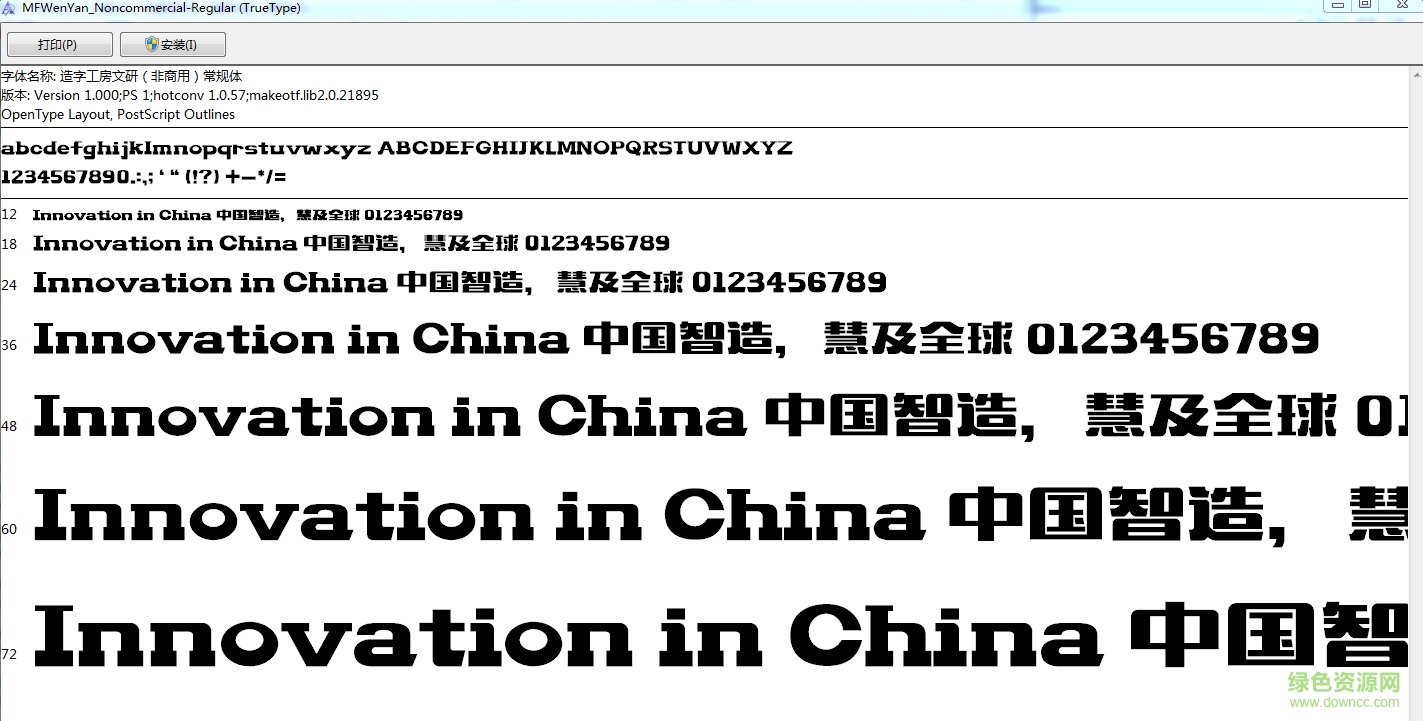
造字工房文研體是一款造字工房類粗黑風(fēng)格字體軟件,文研體給人非常古典浪漫的感覺(jué),十分醒目,適合各大標(biāo)題設(shè)計(jì),也深受廣大書法家的喜愛(ài),還有更多好看字體盡情期待,歡迎到綠色資源網(wǎng)下載體驗(yàn)!
造字工房文研體字形筆畫粗大、平直,讓整體字形更顯干練!精細(xì)的筆畫間凸顯匠師精雕細(xì)琢之力,柔中兼剛不失韌勁。是一款獨(dú)具特色的字體產(chǎn)品!極其適用于科技產(chǎn)品的品牌形象擴(kuò)展。